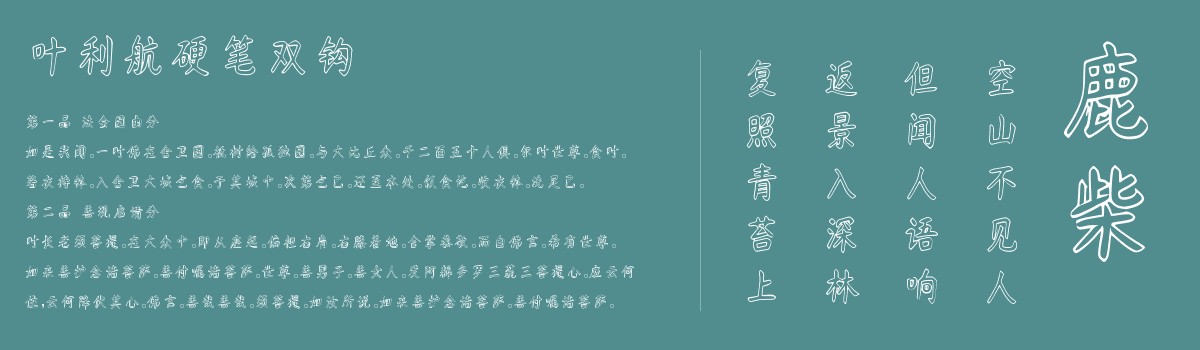
叶利航硬笔双钩
叶利航硬笔双钩是一款由字体家AI神笔造字生成的艺术字体,此字体为空心双钩轮廓,线条均匀挺括。起收笔利落无顿挫,转折处方正刚劲,如刀削般分明。结构紧凑重心平稳,骨架感极强,笔画走向遵循硬笔书写规律,横平竖直间透着规整。空心内部留白利落,与外部线条形成鲜明对比,整体流畅清晰,兼具硬笔的刚健与双钩的规整,刚柔相济,展现出利落又不失秩序的美感。适合用于一些广告标题、平面文案、海报标题、网页广告用字的编辑。